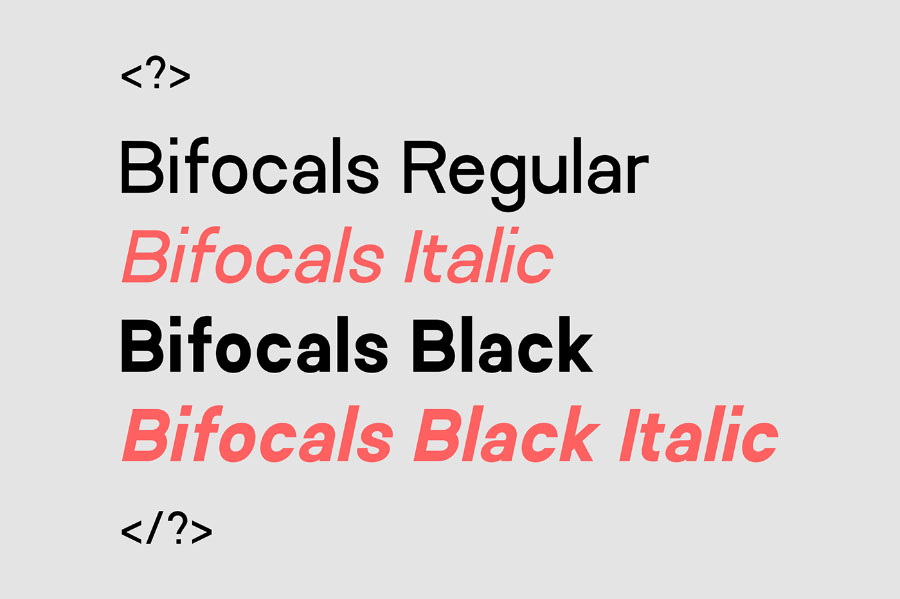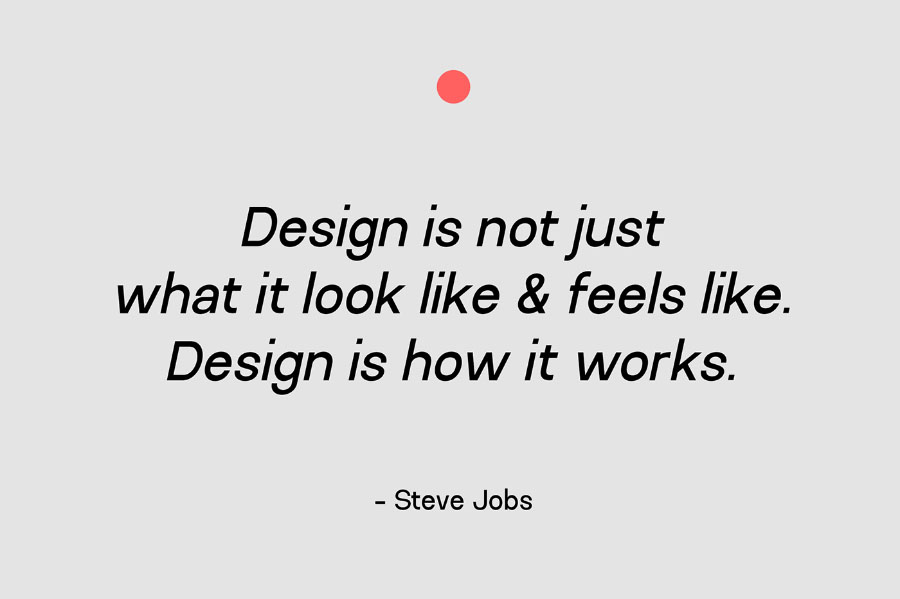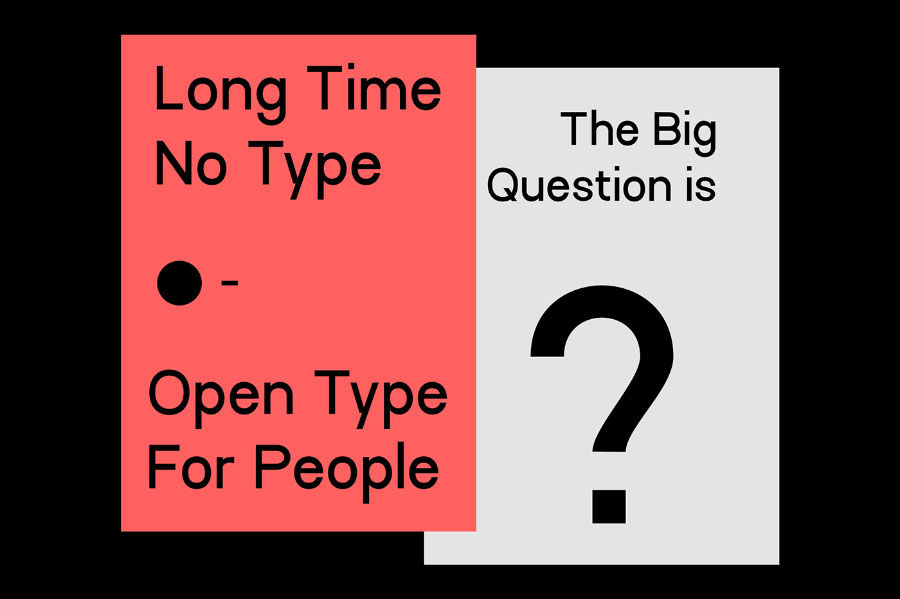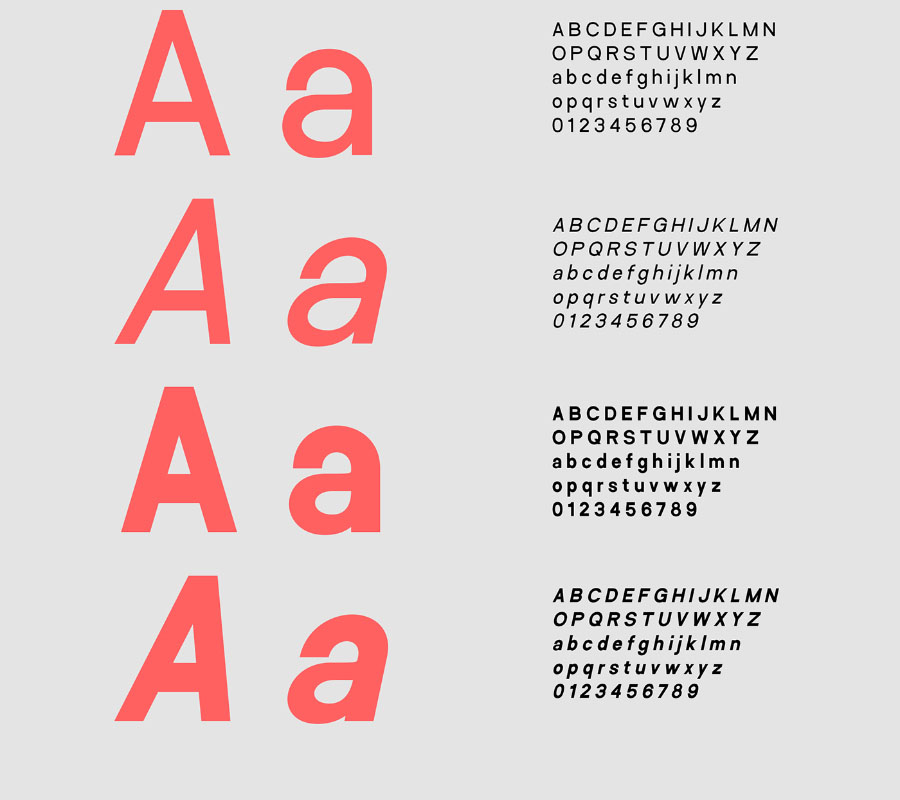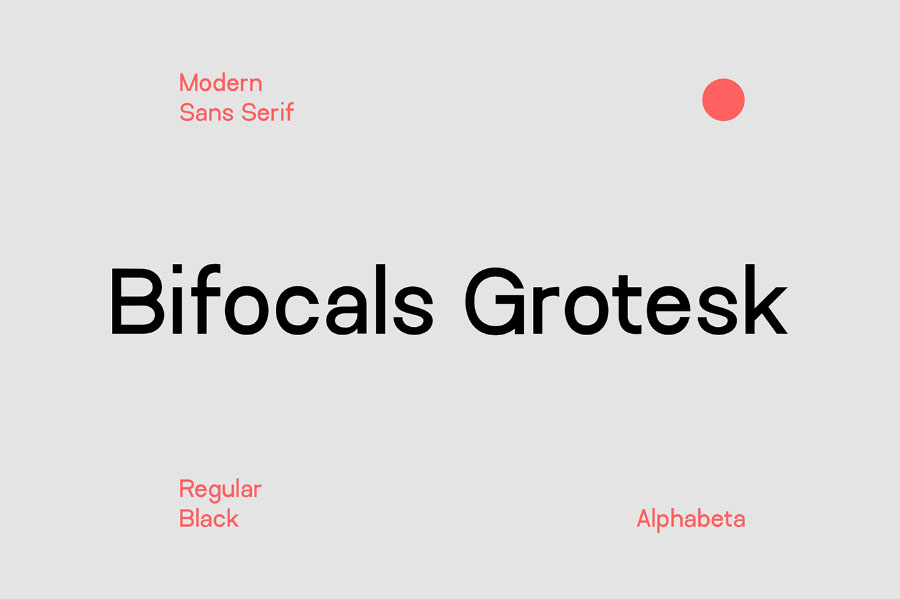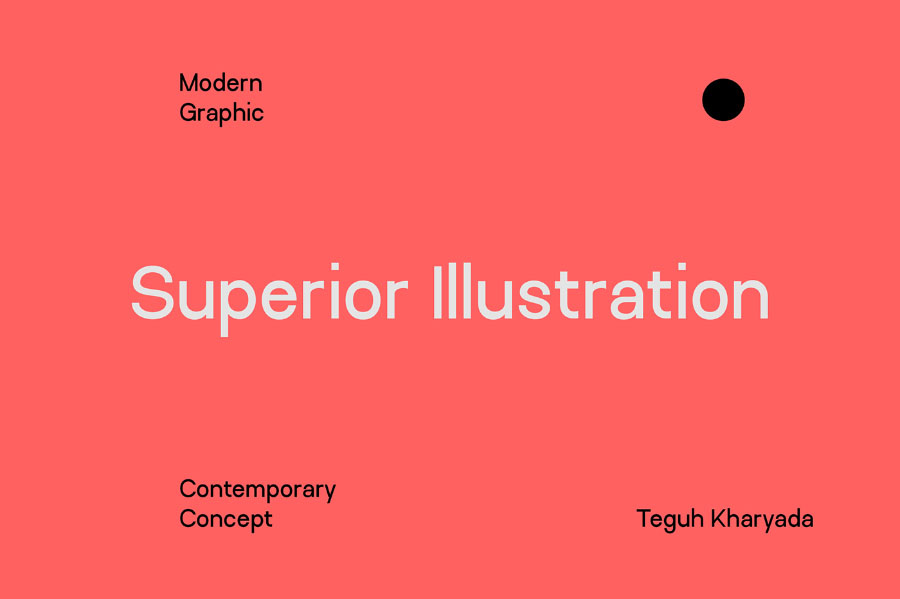
艺术作品免费字体和插图
Artework Free Font and Illustration
Artework免费字体和插图是一个设计师包,其中包括Bifocals Grotesk和10高级插图。受简约,几何和当代艺术的启发。合作艺术品,哈比卜Otang和Teguh Kharyanda。 Bifocals Grotesk来自Habib Otang的几何和现代概念。灵感来自现代风格和工业时代印刷和平面设计。此外,它有4个家庭混合和匹配您的设计。
另外,高级插画本身也是由Teguh Kharyanda提出的当代概念。